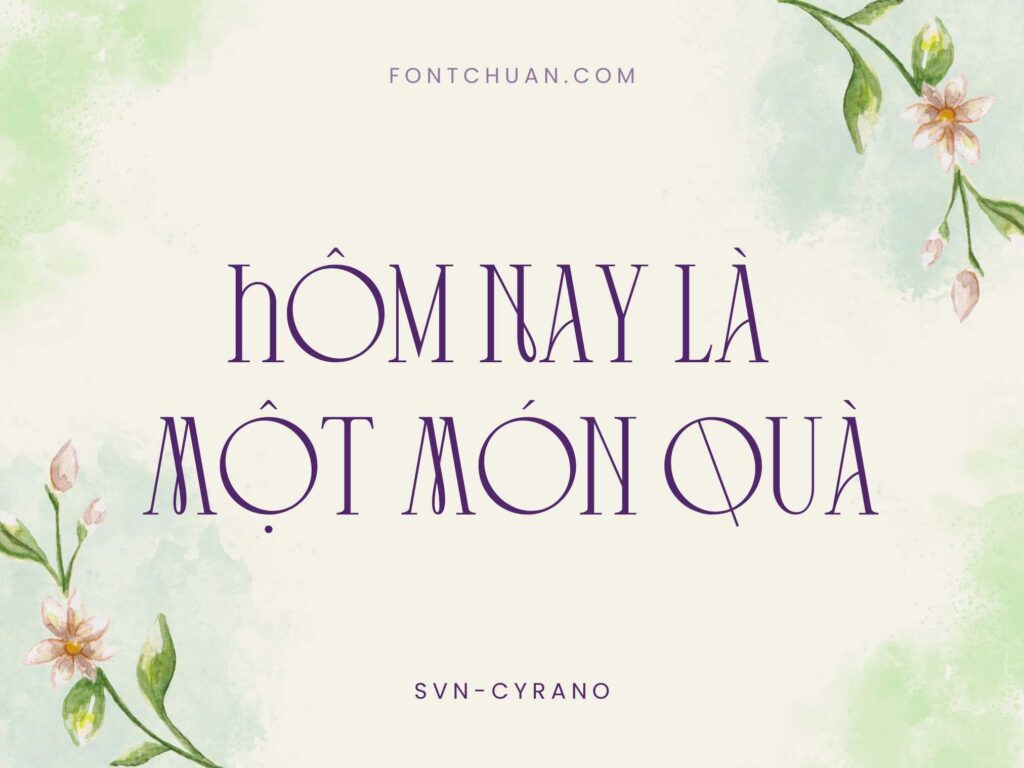
Font SVN Cyrano Việt Hóa
Tác giả Font: Jamaludin Ahmad Sahestya Dharma
Cyrano là một font chữ serif độc đáo, được thiết kế bởi Dharmas Studio. Mỗi ký tự trong font này được chăm chút tỉ mỉ, tạo nên vẻ thanh lịch và chuyên nghiệp. Font này đã được Việt hóa để hỗ trợ tiếng Việt bởi Styleno.1 Fonts, đồng thời hỗ trợ nhiều ngôn ngữ khác, giúp mở rộng phạm vi sử dụng trên toàn cầu. Font này được thành viên của Font Chuẩn sưu tầm và chia sẻ, đáp ứng nhu cầu của bạn đọc và ứng dụng thực tế vào các dự án thiết kế.
Đặc điểm thiết kế của Cyrano bao gồm các đường nét serif tinh tế, mang lại sự thanh lịch và hiện đại cho văn bản. Font này phù hợp cho các ứng dụng như thiết kế logo, tiêu đề, nhãn mác và các dự án sáng tạo khác. Các ngành nghề phù hợp bao gồm quảng cáo, nghệ thuật và thiết kế đồ họa.